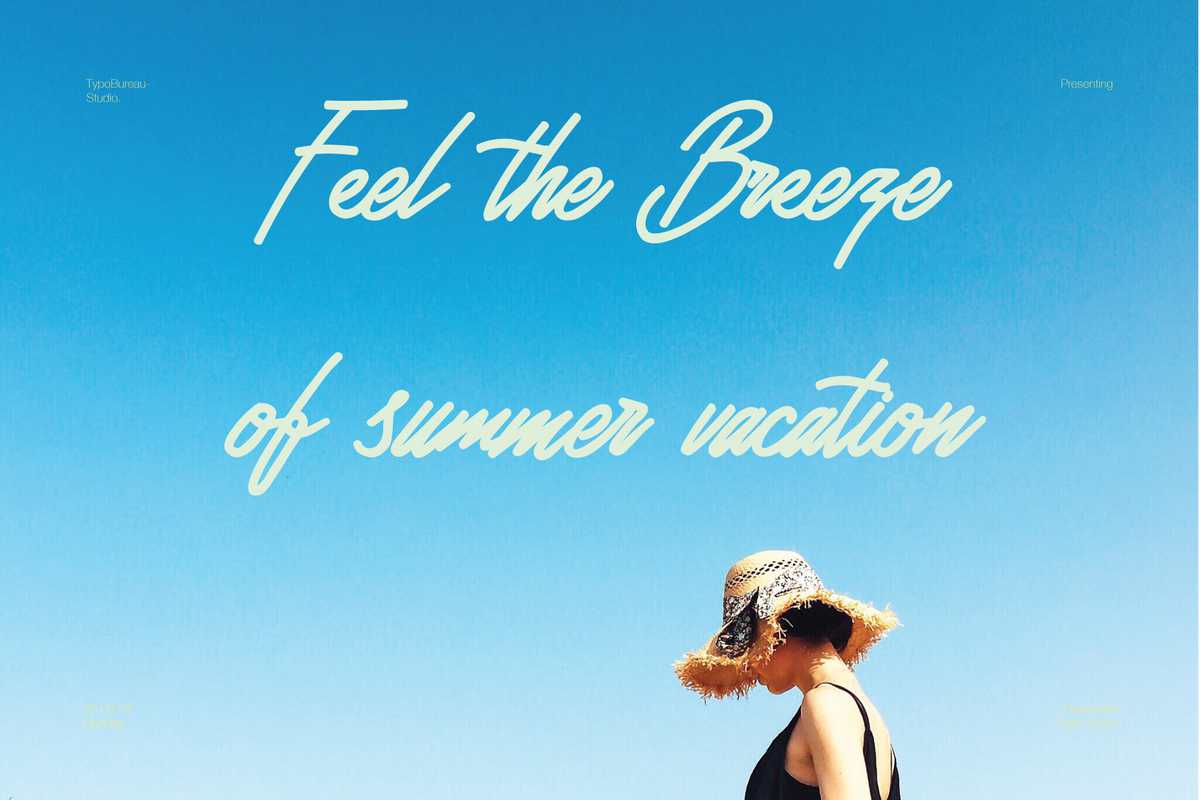
Angkasabiru是一种随意的文字字体,Angkasabiru是一种印度尼西亚语言,它的意思是“蓝色空气”,是由夏末节所激发出来的,让人感到放松和放松。同样,你的设计作品和夏末的感觉也是如此。Angkasabiru是一种随意的文字字体,Angkasabiru是一种印度尼西亚语言,它的意思是“蓝色空气”,是由夏末节激发出来的,它能让你感到放松和放松。同样,也能让你的指定工作和感受夏末节的快乐。